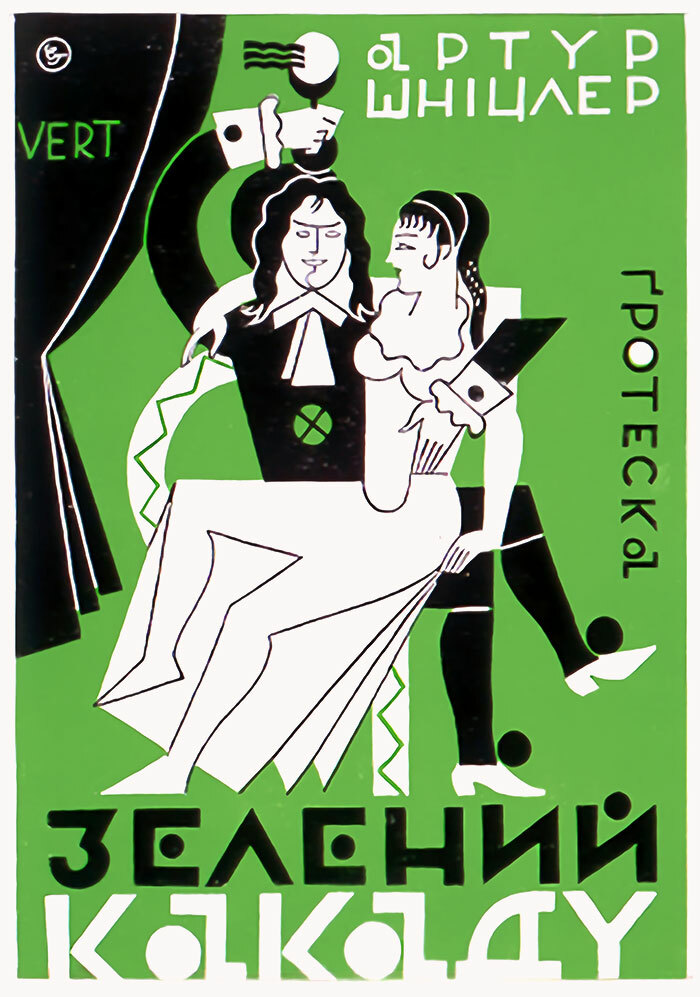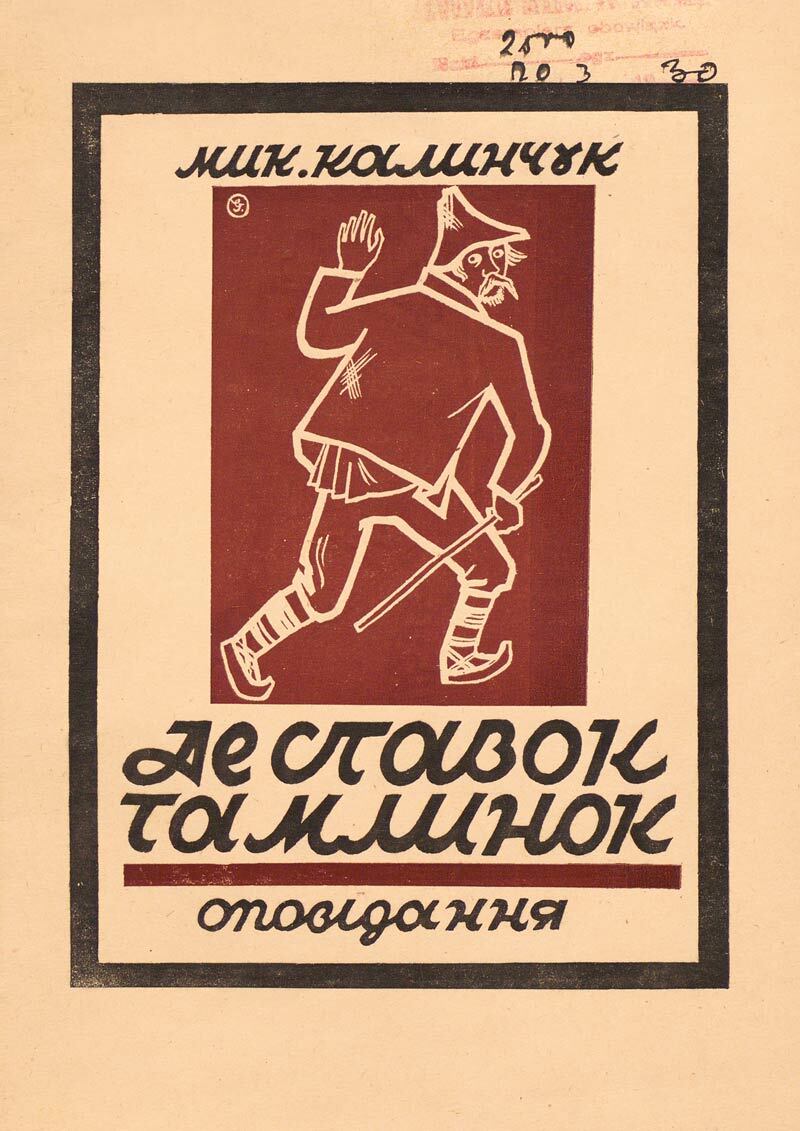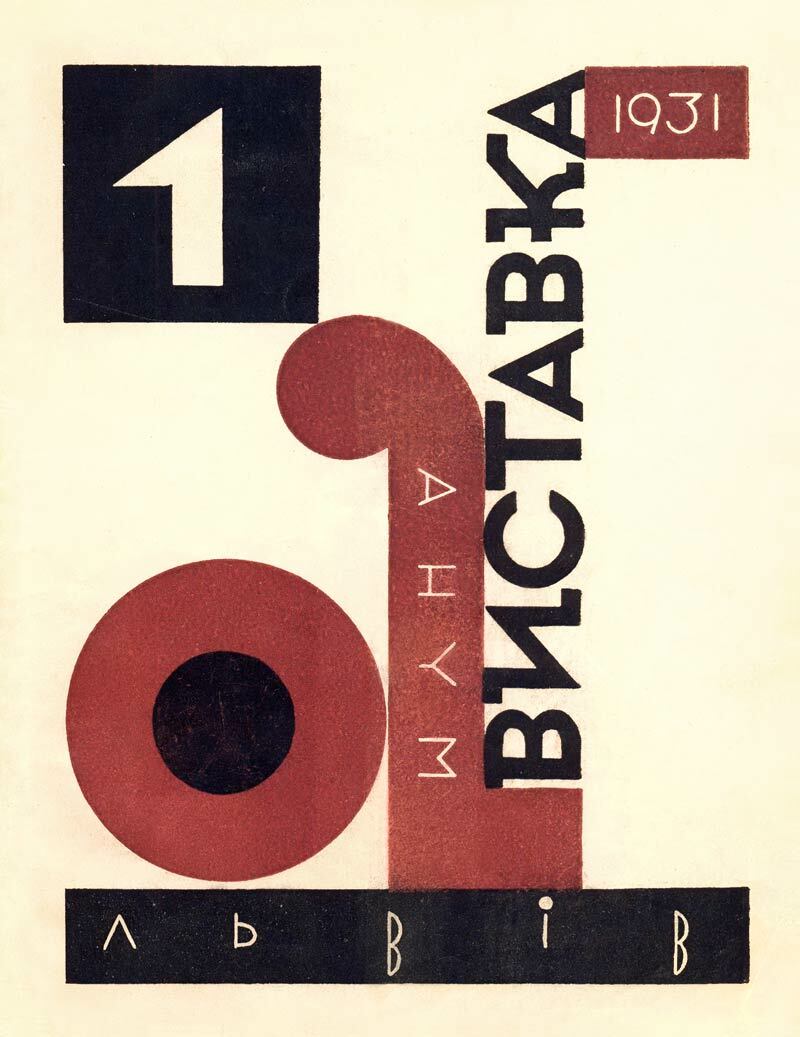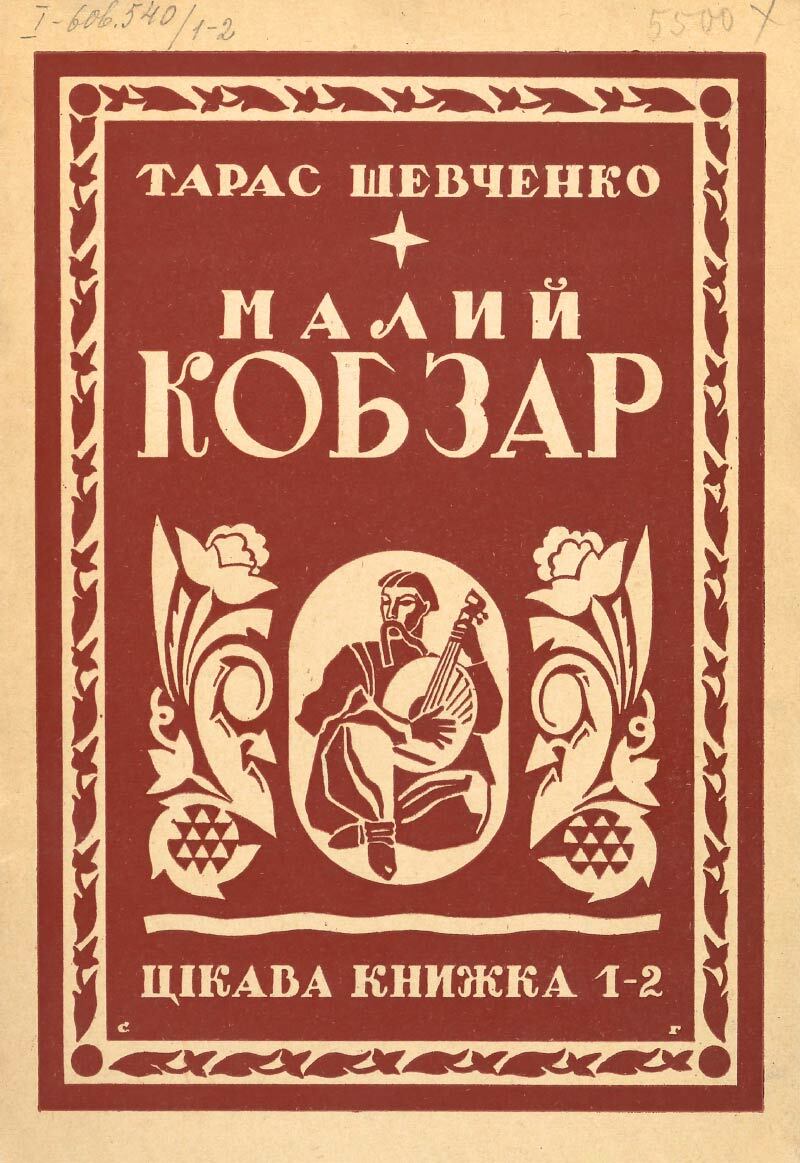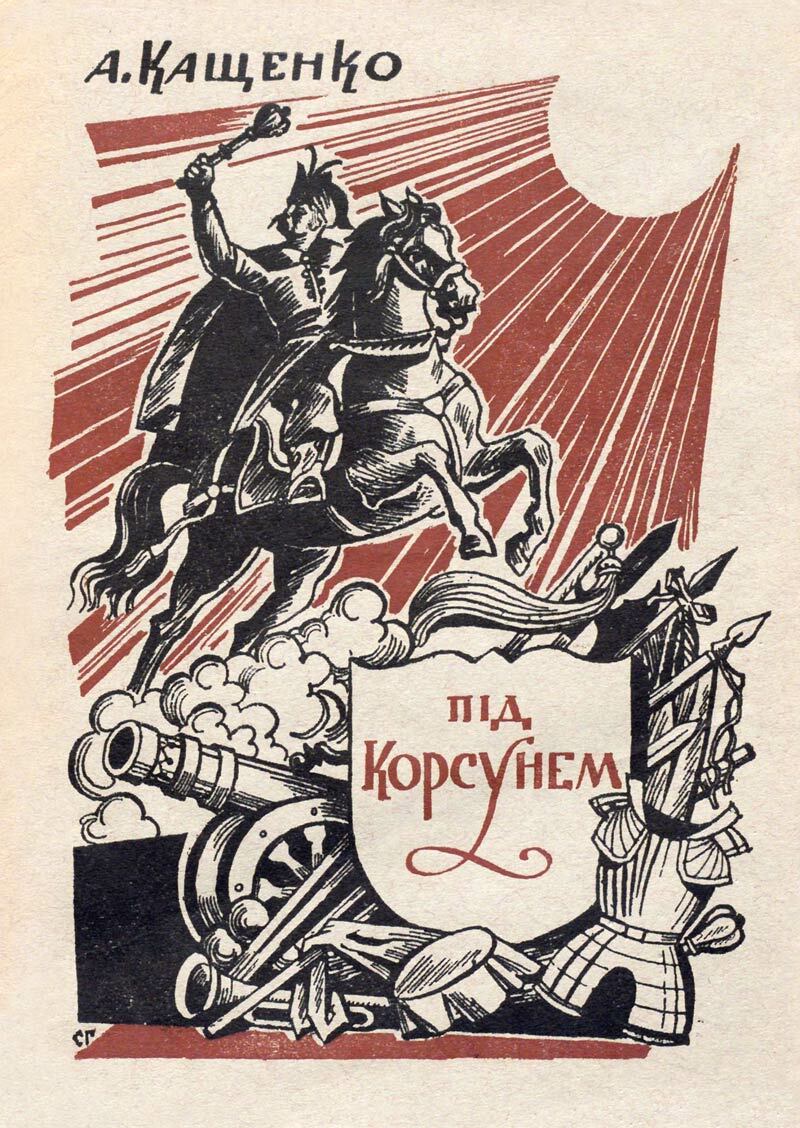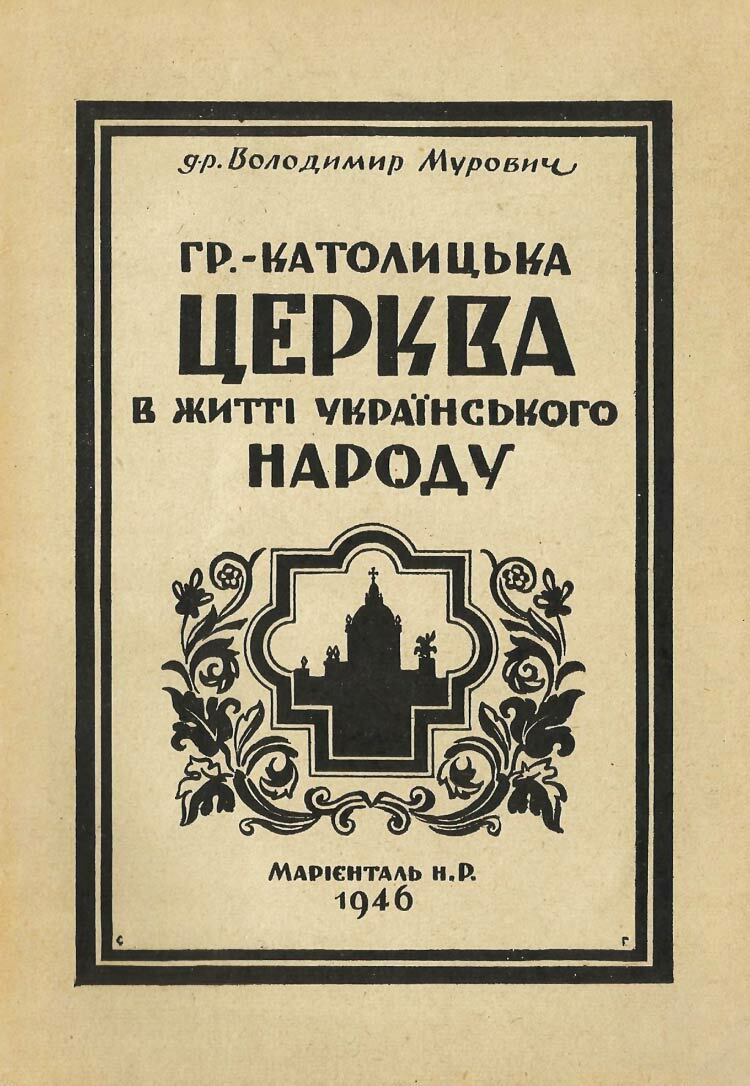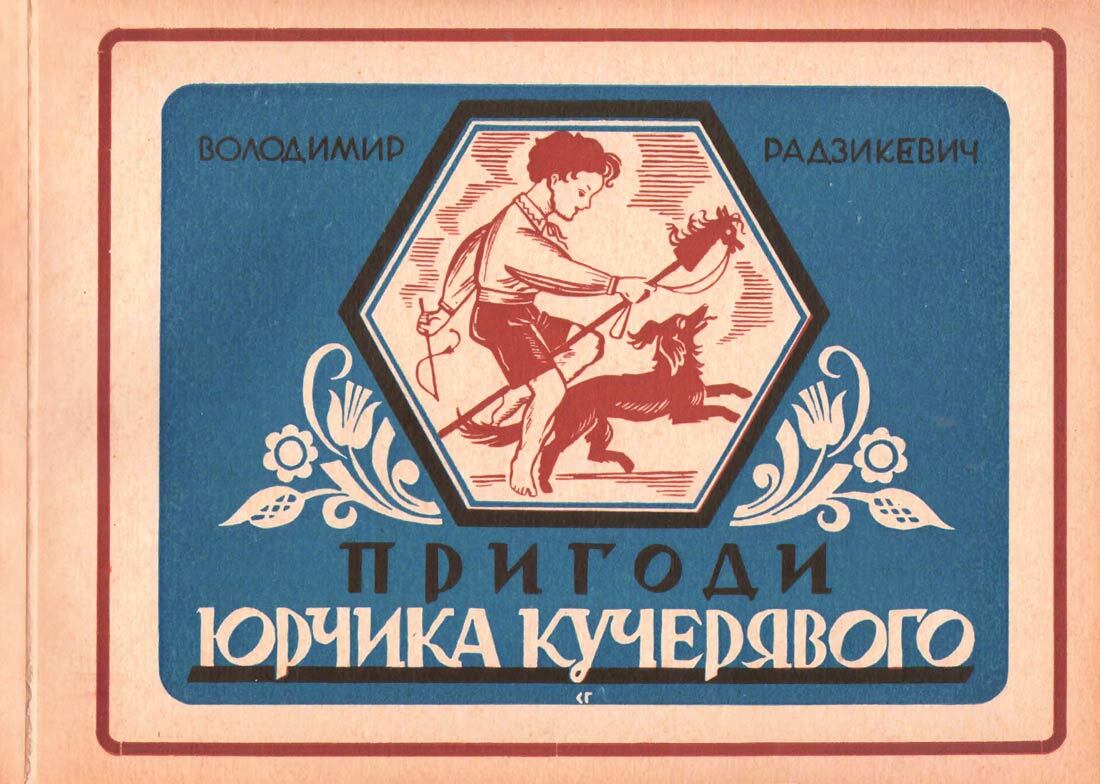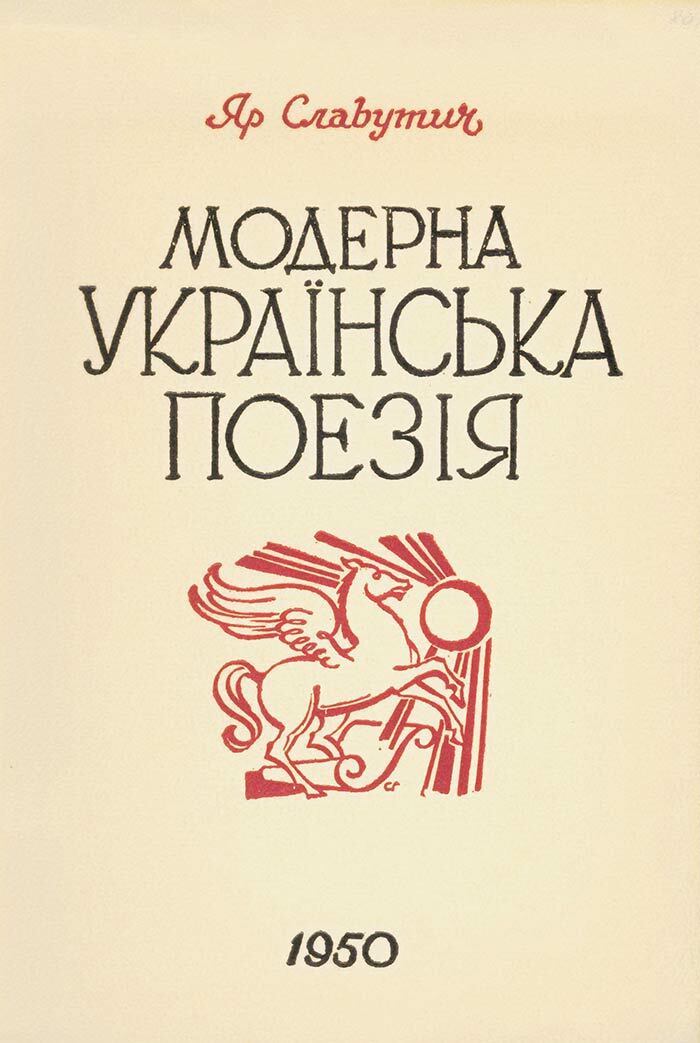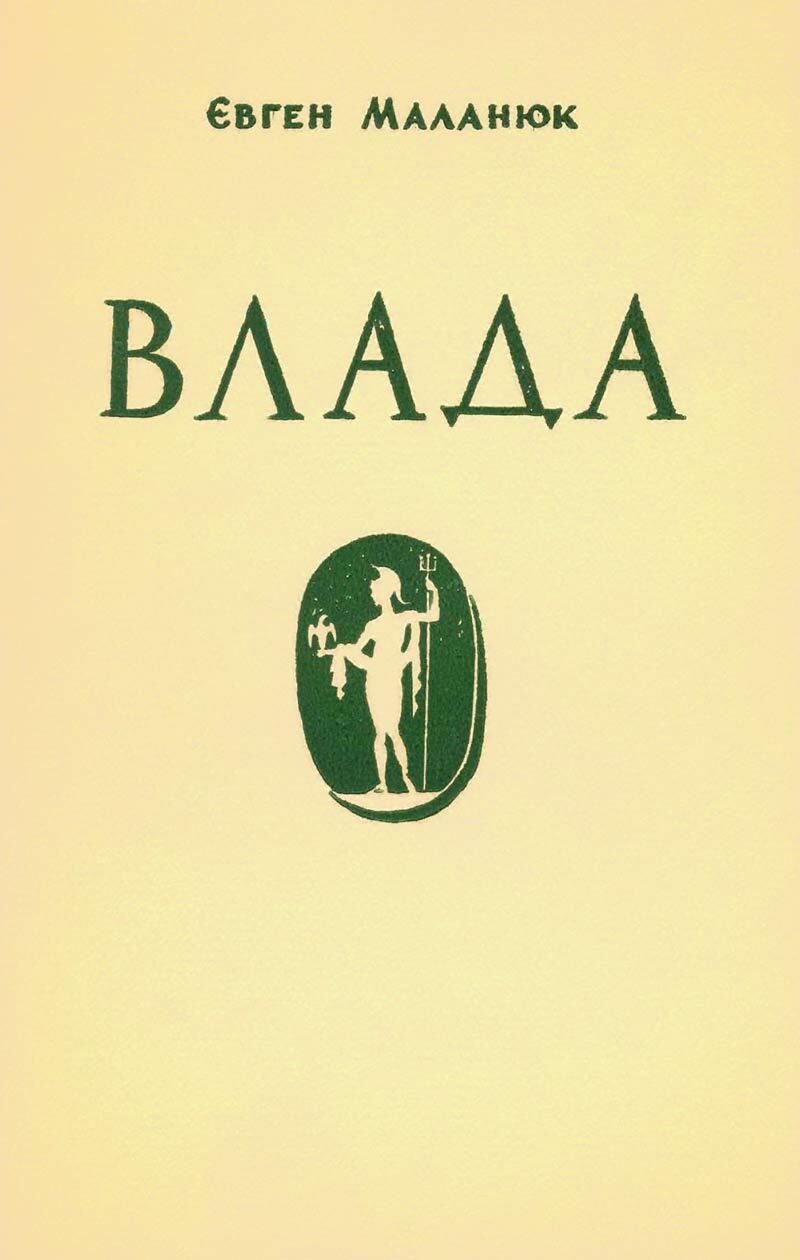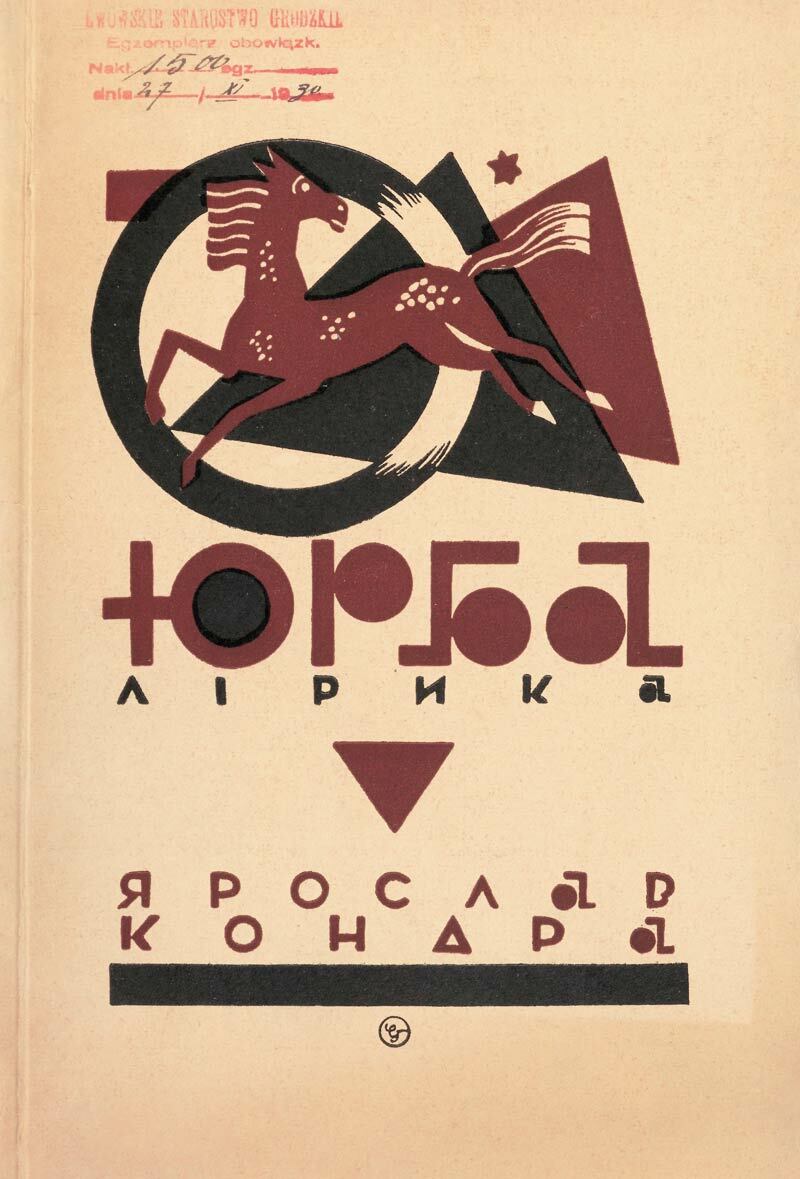
Святослав Гординський (1906–1993)
Святослав Ярославович Гординський народився у 1906 році у м. Коломия. Навчався у мистецькій школі О. Новаківського у Львові. Згодом продовжив освіту в Академії Мистецтв у Берліні (1928) та в академії Жуліана в Парижі (від 1929). У 1931 повернувся до Львова і став одним з ініціаторів створення Асоціації незалежних українських митців, був редактором журналу «Мистецтво» та співредактором літературно-мистецького двотижневика «Назустріч», «Наші дні». У 1939 перед вступом у Львів радянських військ переїхав до Кракова. Після 2-ї світової війни перебував у таборах для переміщених осіб у Мюнхені, згодом (1949) переселився до США (м. Верона). Помер у 1993 у м.Верона, Нью-Джерсі.
1951 рік
Книжкова обкладинка. Літерація, ілюстрація. Святослав Гординський, 1951, Філадельфія.
1950 рік
Книжкова обкладинка. Літерація, ілюстрація. Святослав Гординський, 1950, Філадельфія.
1948 рік
Книжкова обкладинка. Літерація, ілюстрація. Святослав Гординський, 1948, Авґсбурґ.
1946 рік
Книжкова обкладинка. Літерація, ілюстрація. Святослав Гординський, 1946, Марієнталь.
1943 рік
Книжкова обкладинка. Літерація, ілюстрація. Святослав Гординський, 1943, Краків, Львів.
1937 рік
Книжкова обкладинка. Літерація, ілюстрація. Кобзар. Святослав Гординський, 1937, Львів.
1931 рік
Книжкова обкладинка. Літерація в стилі конструктивізм, ілюстрація. Святослав Гординський, 1931, Львів.
Обкладинка каталогу виставки АНУМ. Конструктивістська типографічна композиція. Святослав Гординський, 1931, Львів.
1930 рік
Книжкова обкладинка. Літерація, ілюстрація. Святослав Гординський, 1930, Львів.
Книжкова обкладинка. Літерація в стилі конструктивізм, ілюстрація. Святослав Гординський, 1930, Львів.